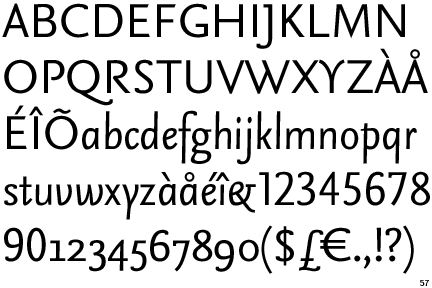
für das Thema Zukunft der Medien ist eine Logoschrift mit diesen Eigenschaften gesucht:
• 4 Buchstaben nach Punkten
• breit laufend
• grotesk
Die Schrift soll Bewegung vermitteln (links nach rechts), als würde sie auf den rechten Rand zusteuern,. Also nicht verharren, wie dies bei ausgeprägter Versalhöhe der Fall wäre. Kursiv oder jedwede Neigung ist tabu.
Was könnte da passen?
Die Scala Sans … warum auch immer kein Schriftmuster eingefügt werden kann.
wenn es sich um ein logo und nur um vier buchstaben handelt, dann würde ich es extra zeichnen, es geht schnelle als sich hunderts schriften anzuschauen und man kann alles beinflussen.
vielleicht wäre die AUTO von underware passend? die AUTO 3 hat eine gerade italic.
Herzlichen Dank für die hilfreichen Antworten. Ich schwanke noch zwischen ScalaSans und Auto3.
Die Legacy finde ich fürs Thema ein wenig zu verspielt und in der Strichstärke zu dünn. Die Auto hat den stärksten Zug nach rechts, ist etwas verspielter als die Scala, dafür "frischer". Übrigens chaotische Seite, die Underware. Man findet auf den ersten Klick keine Schriftübersicht. Macht man das jetzt so?
Selber machen wäre auch mein Favorit. Wenn nicht: Seria Sans hat auch eine aufrechte Italic.
Die SeriaSans Bold Italic Capitals ist es dann geworden. Aufrechte Italic - wusste ich gar nicht, dass es so etwas gibt. Stark - hat alle Ingredienzien, die ich mir vorgestellt habe.